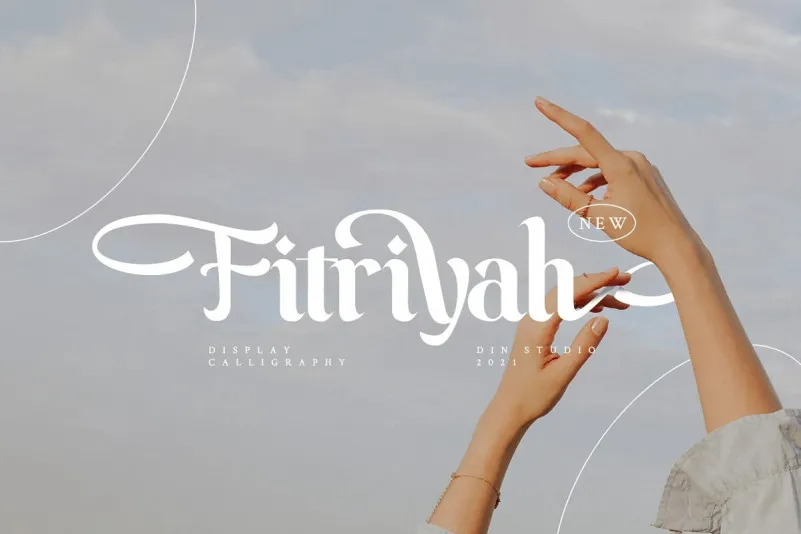
Fitriyah font
A ‘Fitriyah’ é uma fonte ideal para quem busca uma beleza exuberante que vai ao encontro dos seus projetos criativos. Esta fonte exalta sua imaginação, com seu design especializado e alternativas únicas de letras, permitindo-lhe criar belas mensagens finais. Não perca tempo, essa maravilhosa fonte é agora sua! Criada sob medida para preencher todos os seus desejos, ela é particularmente adequada para posts nas redes sociais e anúncios, citações impressas, designs de camisetas, embalagens ou como overlay moderno ao fundo de qualquer imagem. Aproveite essa oportunidade única, a ‘Fitriyah’ está à sua espera!